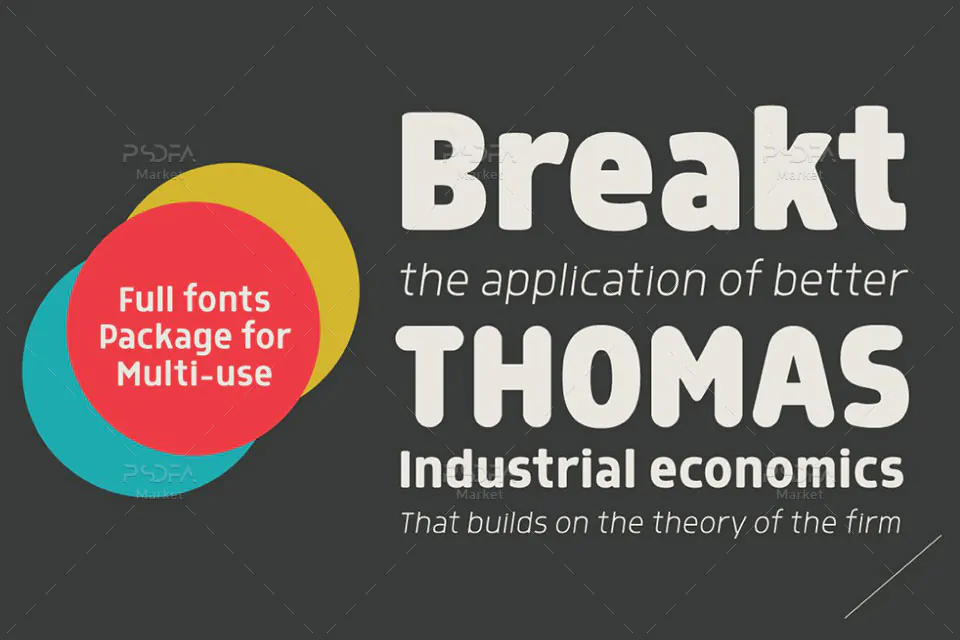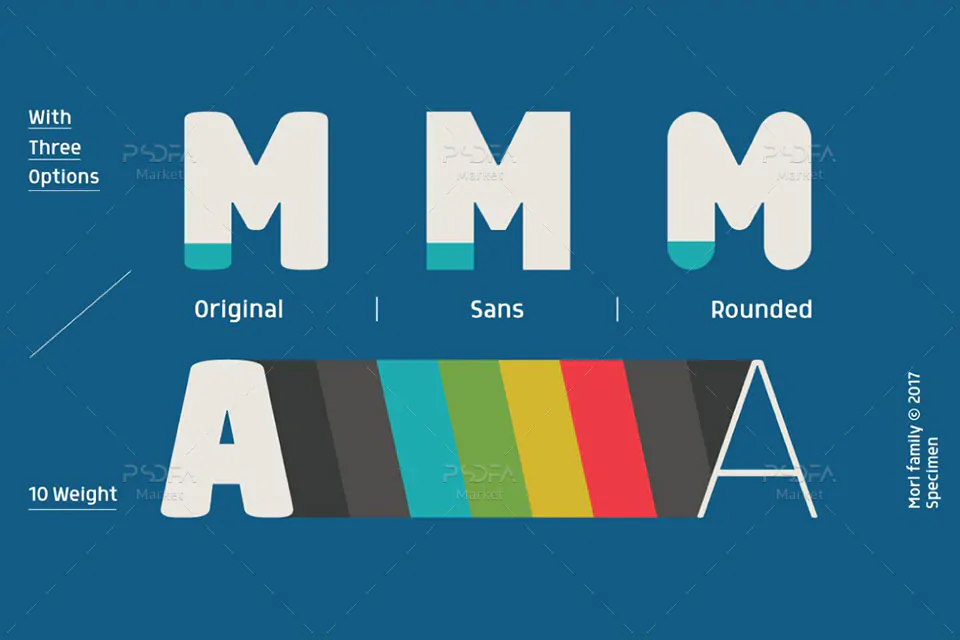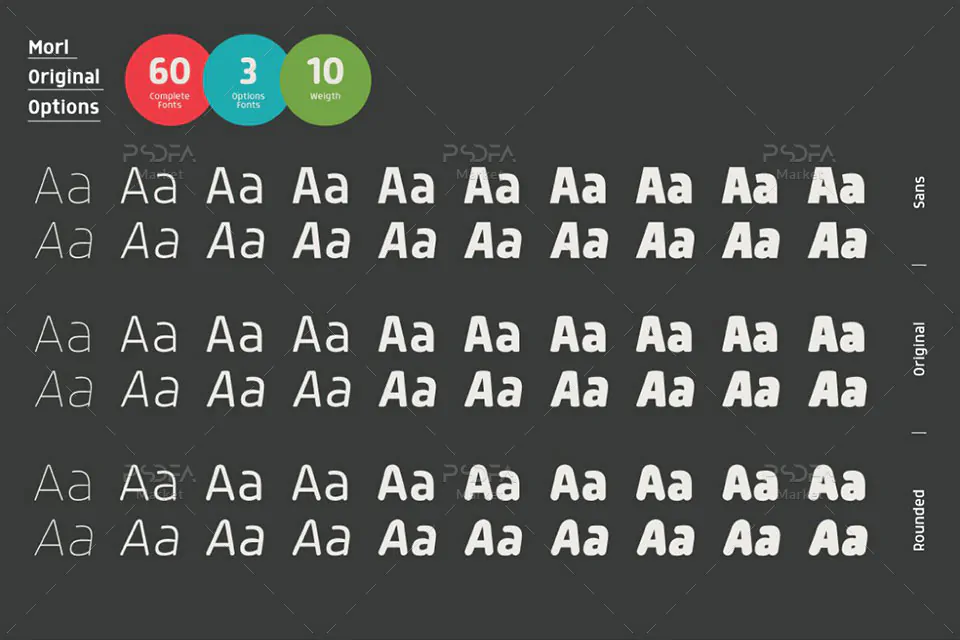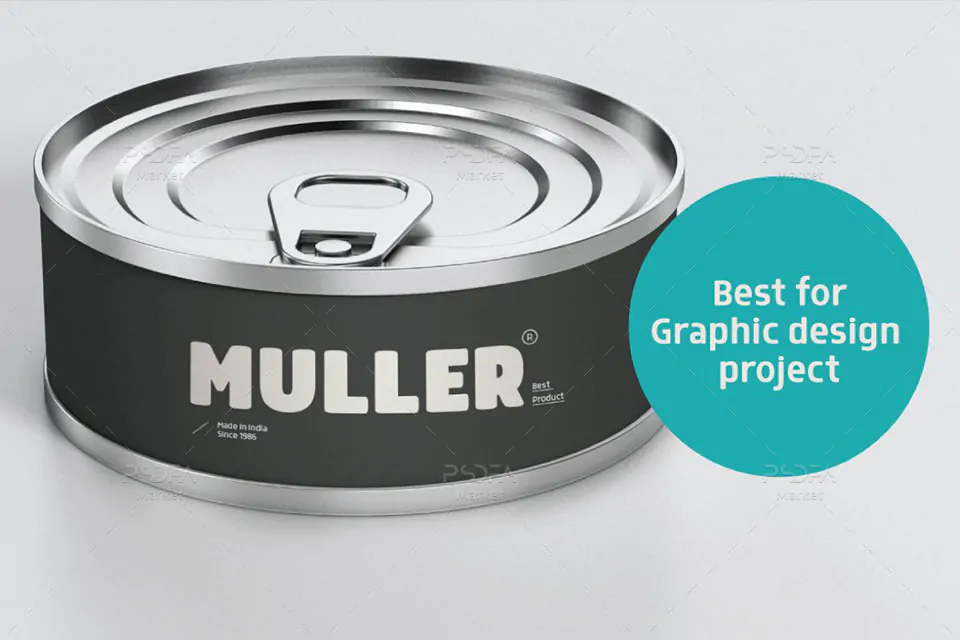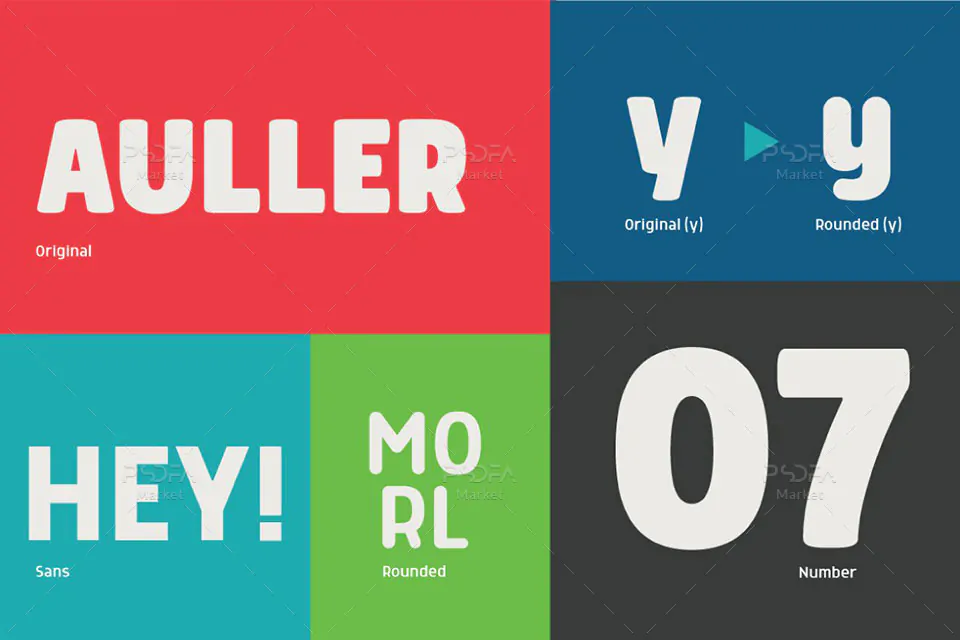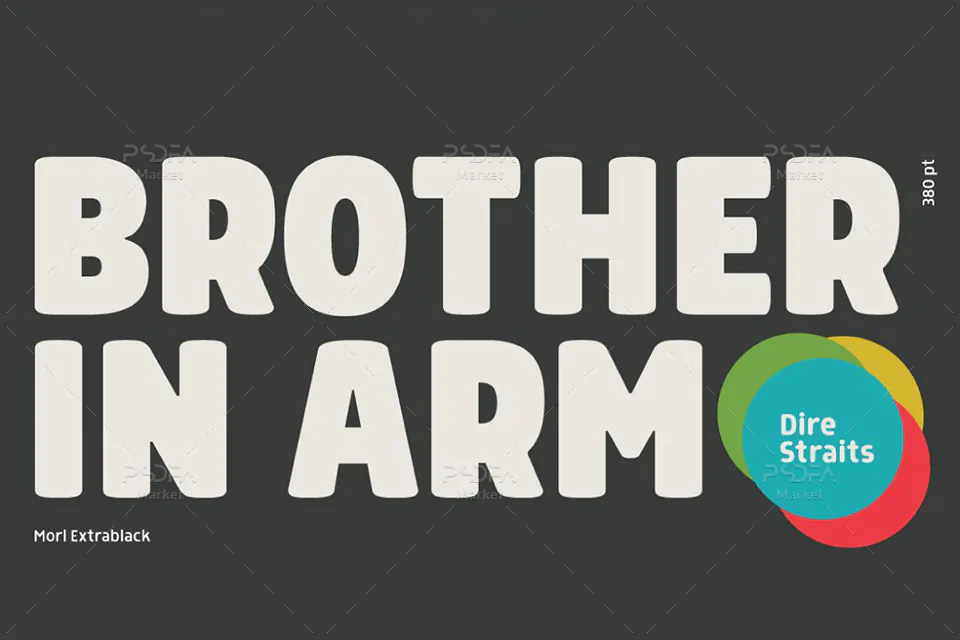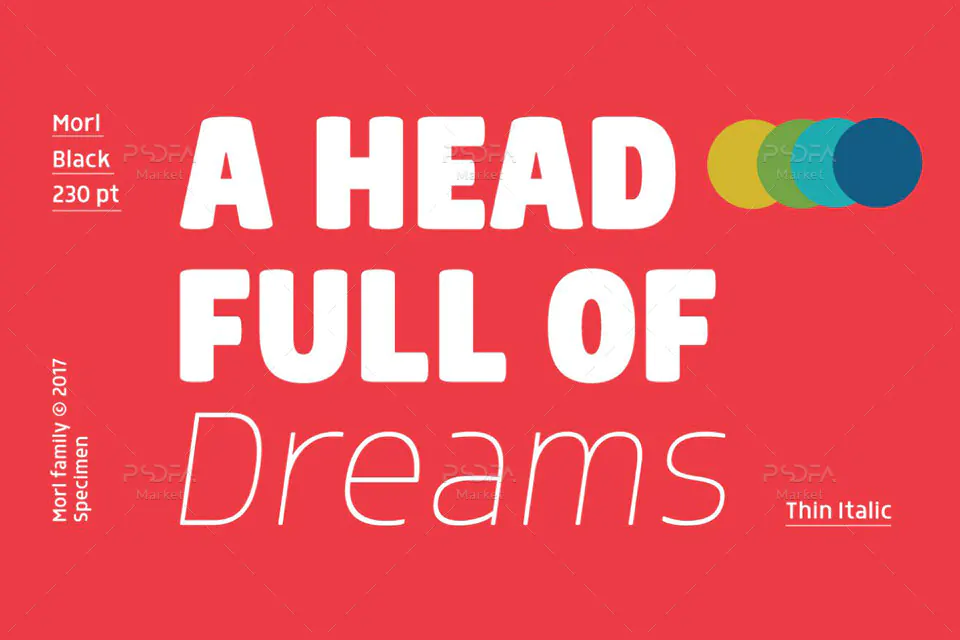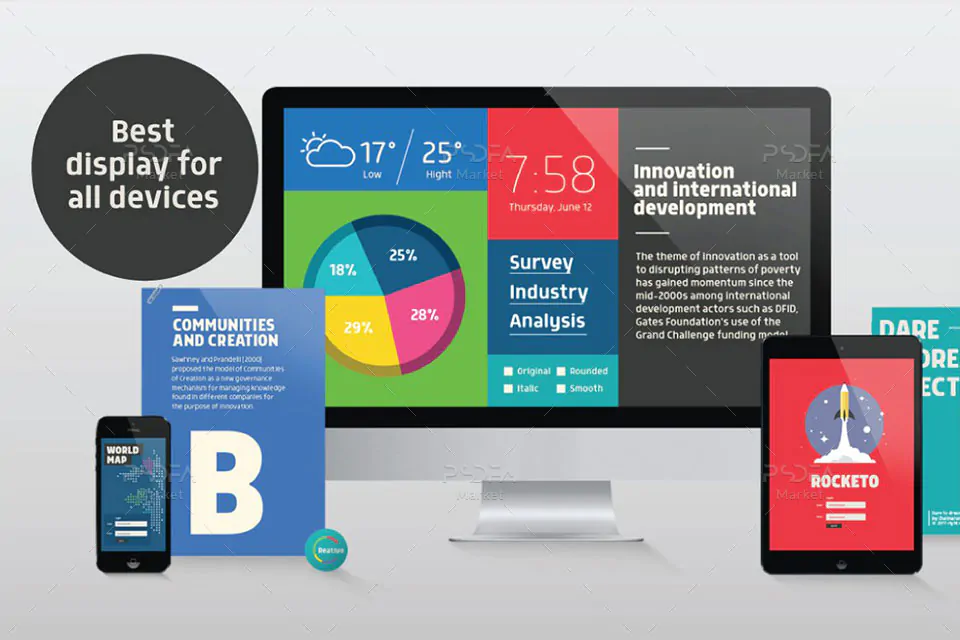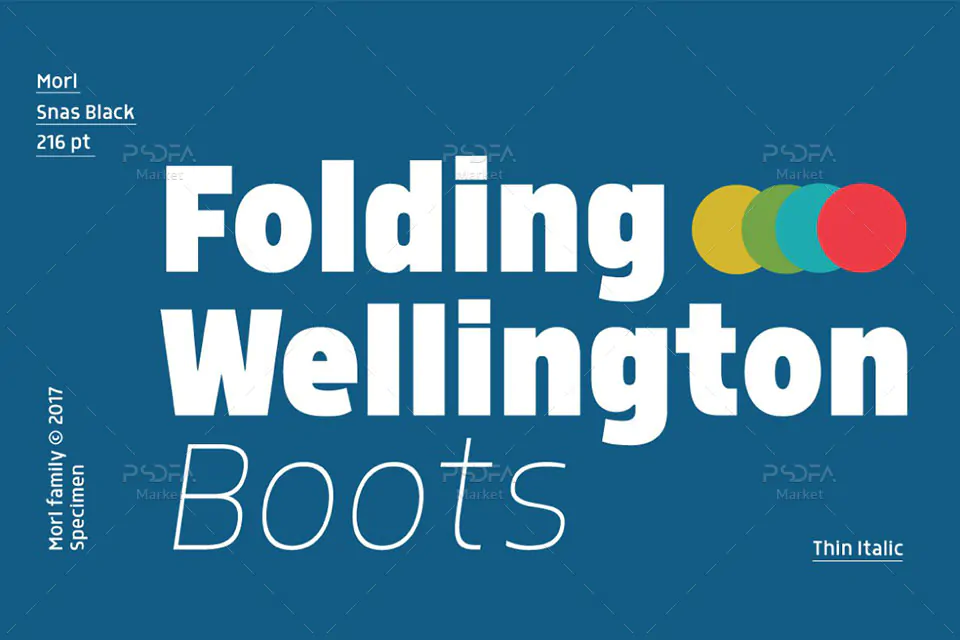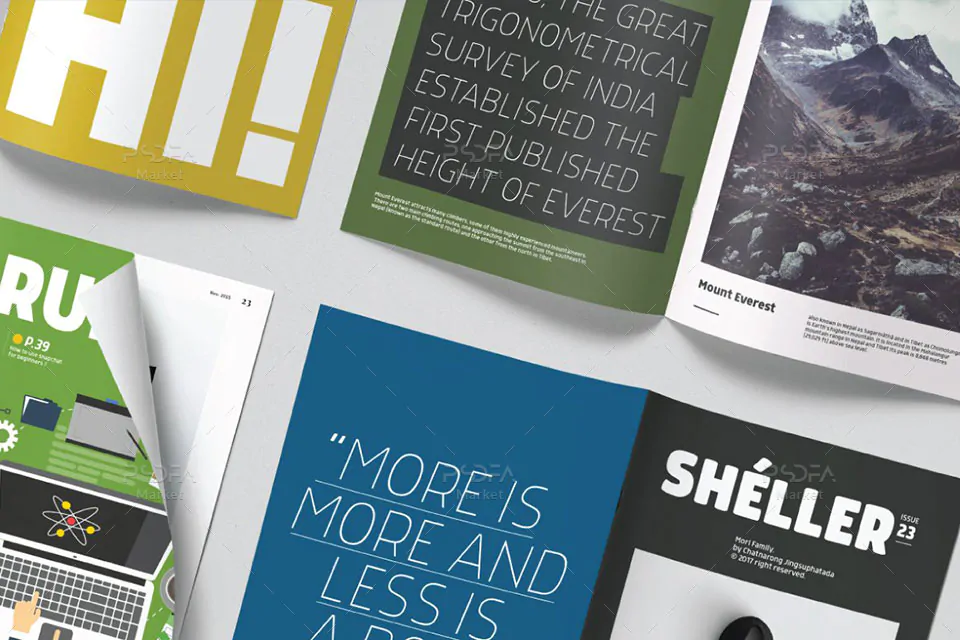
در این مطلب شاهد فونت انگلیسی فوق العاده زیبای Morl می باشید. این فونت که با دو فرمت ttf و otf در سایت قرار داده شده است از دسته فونت هایی است که مناسب جهت طراحی های گرافیکی به خصوص طراحی انواع پوستر و همچنین مناسب جهت تایپ در نرم افزارهای ویرایش متن از جمله مجموعه نرم افزار آفیس و … می باشد. این فونت انگلیسی که از خانواده فونت Morl می باشد دارای 60 نوع فونت است که در سه سبک Original , Sans و Rounded طراحی شده است. پس از دریافت و نصب این مجموعه فونت در سیستم خود می توانید از آن ها در تمام نرم افزارهای گرافیکی و ویرایشگر متن استفاده نمائید. پیش نمایش این فونت زیبا را می توانید در گالری تصاویر زیر مشاهده فرمائید.